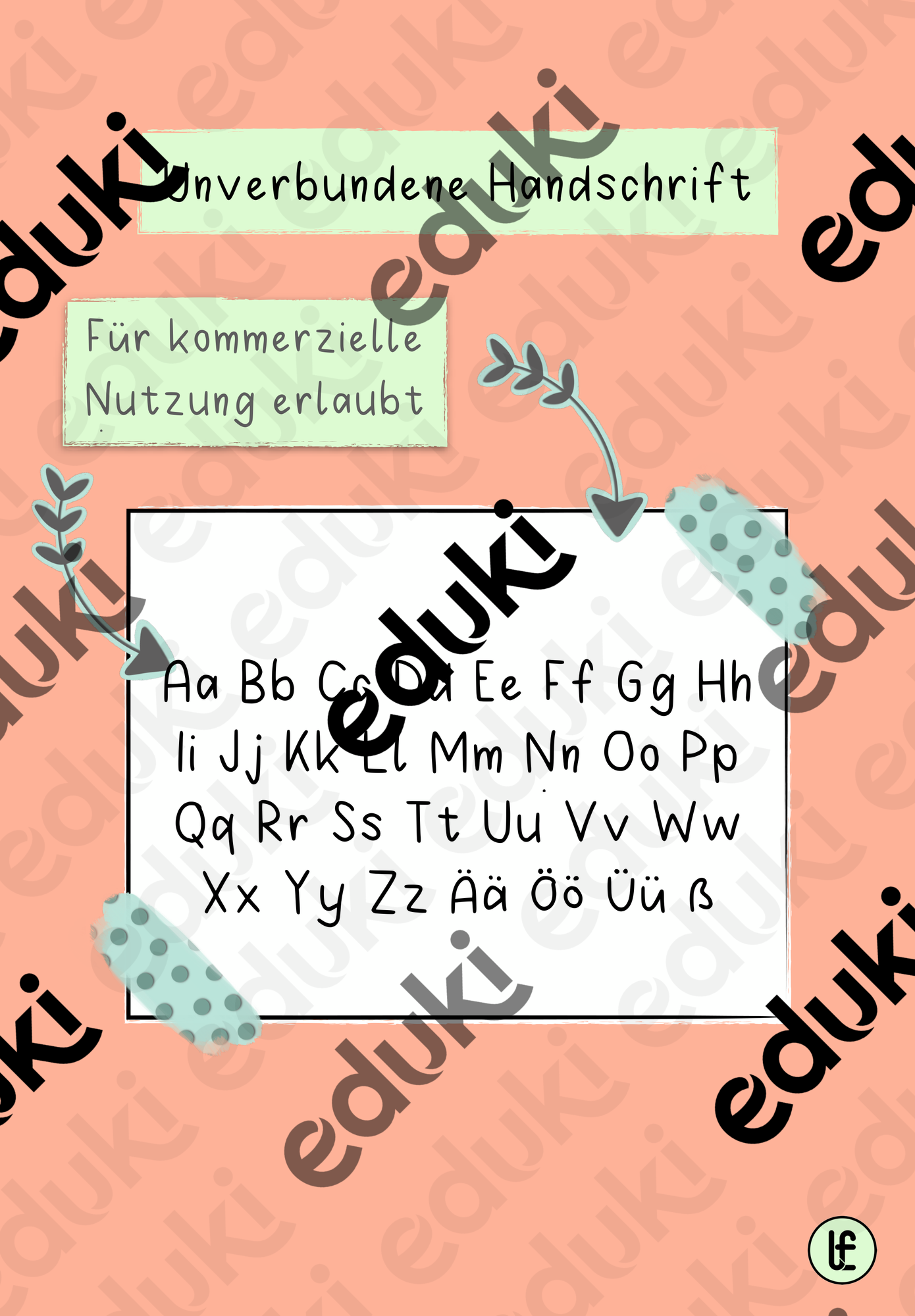
Das Material umfasst eine selbsterstellte Standard Handschrift. Sie ist leicht zu lesen, jedoch keine reine Druckschrift.
Die Schrift ist perfekt um deinem Material, deinen Nachrichten uvm. einen individuellen Touch zu geben.
Schriftart: Standard Handschrift by @lehrerin.franzi